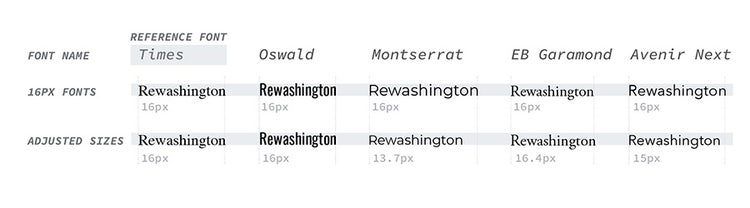
読み手に合わせてフォントをパーソナライズすることが望ましい理由
メール、スライド、あるいはドキュメントを受け取って、送り手の書式の選択に真剣に疑問を持ったことはありませんか?たとえば、フォントが小さすぎたり、装飾が過剰だったり、あるいはただ単に読みにくかった場合です。その際、タイポグラフィの選択が読みやすさに与える強い影響を感じていたかもしれません。3 年にわたる調査・研究を経てアドビが理解したことは、読む行為における個人差がいかに大きいか、理解の仕方がいかに一人ひとり微妙であるか、そしてまだ答えの見つからない疑問がいかに多いかということです。
ACM の Transactions on Computer Human Interaction (TOCHI)に掲載されたアドビの最新の研究論文では、フォントの選択が、一般成人がテキストを読む際のパフォーマンスに与える影響を調査しています。アドビ・リサーチのインターンで筆頭著者の Shaun Wallace と、彼の共同執筆者達は、コミュニケーションにおいてフォントがいかに重要であるかについて、多くを考察しています。この論文は最近、Fast Company の「Are Some Fonts Ageist?」)や、Nielson Norman Group「Best Font for Online Reading: No Single Answer」でも取り上げられました。
注:以下の論文はフォントについて研究したものです。書体とは混同しないでください。書体は、同じデザインを共有する記号や文字や数字のグループです(例えば、Times New Roman)。フォントは、「16pt で太字の Times New Roman」のように特定のスタイルの書体です。
フォントを変更するだけで驚異的なスピードアップ
この調査は、18 歳から 71 歳までの多様な背景を持つ 352 人の参加者を対象に行われました。そのうちの 46% が女性、22% がバイリンガルで、全員が問題なく英語を読めると自己申告しています。この研究では、16 種類の一般的な書体を取り上げて、読む速度、好み、理解度のスコアを測定しました。使われた測定方法は、検眼士の視力検査にヒントを得たものです。検眼士が文字を回転させて「どちらが読みやすいか」を尋ねるように、フォントを交互に切り替えながら、フォントの好みを測定しました。続いて、今読んだ内容の理解を調査するために、多肢選択式の質問を行いました。内容に対する興味や知識についても質問し、彼らの読解パフォーマンスから、こうした要素の影響を排除するために使用しました。
発見したこと
唯一の「最適なフォント」というものは存在しません。読み手によって、理解度を落とさずに最も速く読めるフォントは異なります。すなわち、パーソナライズが重要になります。
• 平均して、最も速いフォントでは、最も遅いフォントよりも 35% 速く読むことができました。(速いフォントと遅いフォントは人によって異なります)
• これによる理解度への影響が見られませんでした。参加者は、どのフォントでも高い(多肢選択式の理解度の確認で約 90%)理解度を示しました。
• すべての被験者にとって、明らかに優れているフォントはありませんでした。将来の読書ツールは、読者がフォント体験をパーソナライズできるようにする必要があるでしょう。
人々が好みだとするフォントが、彼らにとって最も速く読めるフォントと違うことは珍しくありません。人によって好みのフォントは様々ですが、その好みはパフォーマンスとは無関係です。参加者の 73% は、自分の好きなフォントが最も速く読めるフォントだと信じていました。実際には、参加者は、自分の好きなフォントよりも、最も速いフォントで平均 14% 速く読みました。すなわち、人々が最適なフォントを発見するための支援が必要だということになります。
読み手のいくつかの特性、特に年齢は、最適なフォントの予測に有効です。Garamond と Montserrat 書体は、年配の高い参加者により良いパフォーマンスをもたらす傾向がありました。この原因は、特定のフォントに対する慣れや、フォント自体の視覚的特性など、複数の要因の組み合わせが考えられます。
35 歳以上の平均読解速度(ワード/分)をオレンジ色で、それ以外を青色で表示したグラフ。若年層は多くのフォントを平均的に速く読むが、高齢者層は EB Garamond と Montserrat を速く読む。
この驚くべき結果は、さらなる研究の必要性を伝えます。フォントに加えてテキストのフォーマットがどのように影響するか?読解速度や質問による理解度の確認以外のパフォーマンス指標があるか?あるいは、どのような多様性のある参加者の集団でテストすべきかなども気になる点です。また、読者がより速く読めるようになる最適なフォーマットを提供するツールへのニーズも示唆されています。
アドビが創設メンバーである The Readability Consortium では、すでに読みやすさに関するフォローアップ調査が、子供、成人、失読症を持つ読者を対象に始められています。その一つは、文字の幅、太さ、間隔などのテキストの特性の研究です。また、ハイライトや下線によって、読み手がテキストの行のどこにいるかを把握しやすくする「リーディングルーラー」の効果についても、視線データや音読者の音声記録を収集して、調査が進められています。さらに、スピードと理解度を向上させる最適なフォントフォーマットと読者のマッチングを行うモデルの構築への取り組みもあります。
目指したい未来は、ポケットや机の上のデジタルアシスタントが、個別のニーズ、目、脳に合わせて画面上のテキストを変えられる環境です。これを実現するには、技術者、視覚科学者、データ科学者、タイポグラファー、デザイナー、教育者、読解の専門家、そして、この件に関心を持つすべての人との協力が必要です。次にテキストを画面の中で扱う機会があれば、是非より良い「読む体験」について考えてみてください。